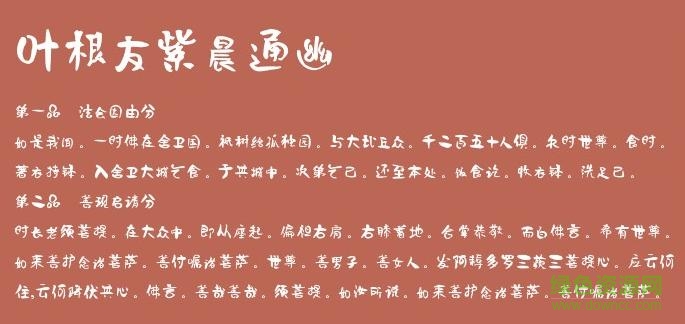
葉根友紫晨通幽字體是一款具有鮮明特色的中文字體,游戲邊角圓潤看上去非常的可愛,適合用來進(jìn)行各種藝術(shù)創(chuàng)作,有需要的朋友歡迎下載使用!
葉根友紫晨通幽是一款個(gè)性時(shí)尚而帶有卡通形態(tài)的字體,字體大小錯(cuò)落有致,活力無限,恰似一款通向詩與遠(yuǎn)方的幽靜物語,是現(xiàn)代快節(jié)奏中具有強(qiáng)烈表現(xiàn)力的漢字字體。